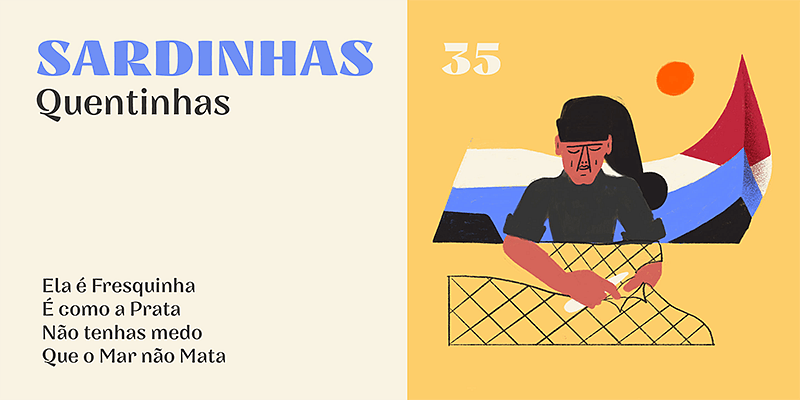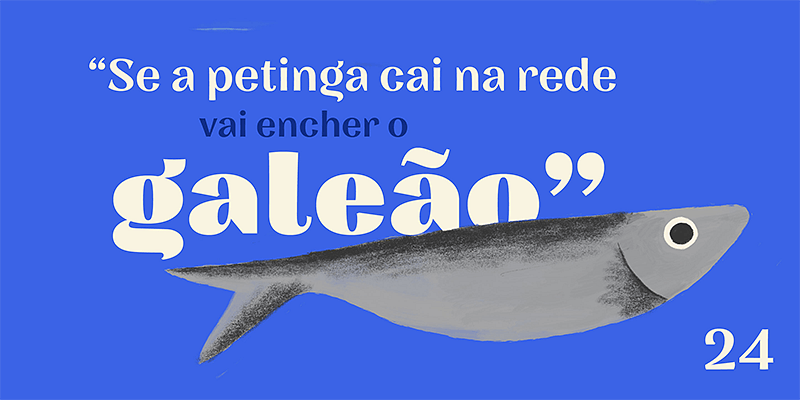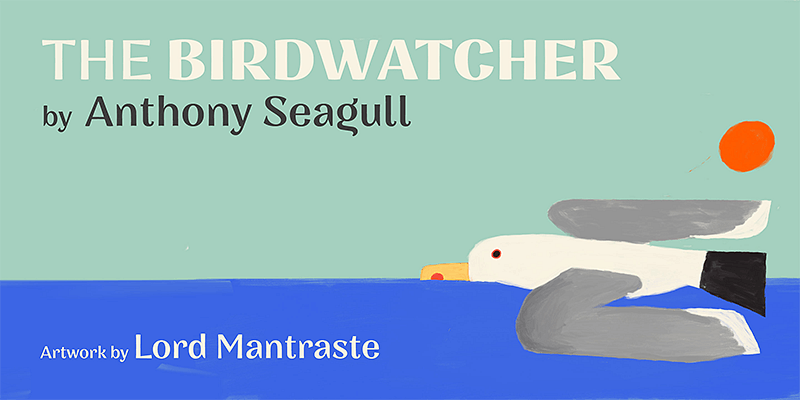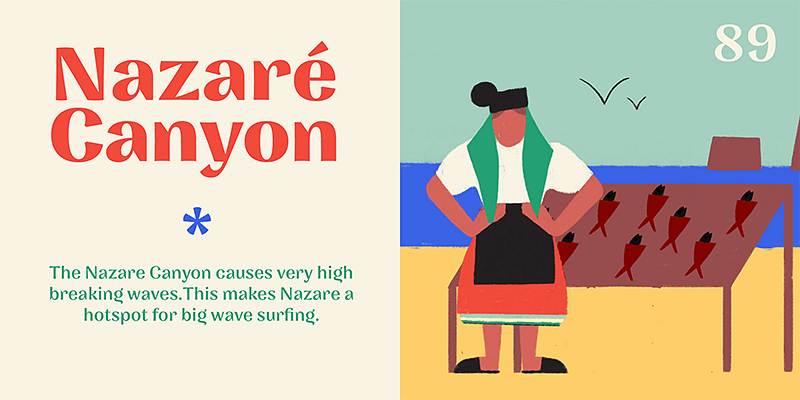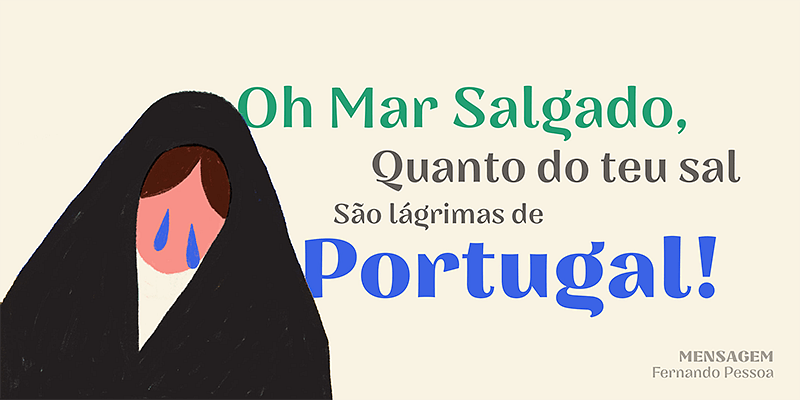
Alles begann mit einer portugiesischen Seifenverpackung aus der ersten Hälfte des 20. Jahrhunderts. Nazaré fällt in die Kategorie der Halbserifen und hat einen großen Kontrast. Sie eignet sich hervorragend als Display-Schrift, besonders in den kräftigeren Schnitten, die noch mehr Kontrast bieten.